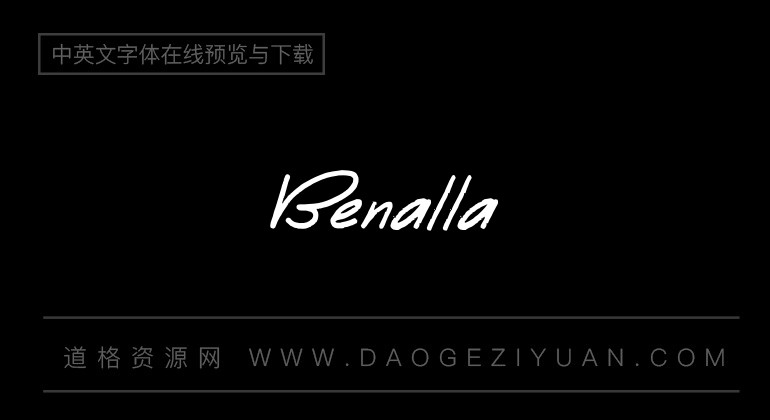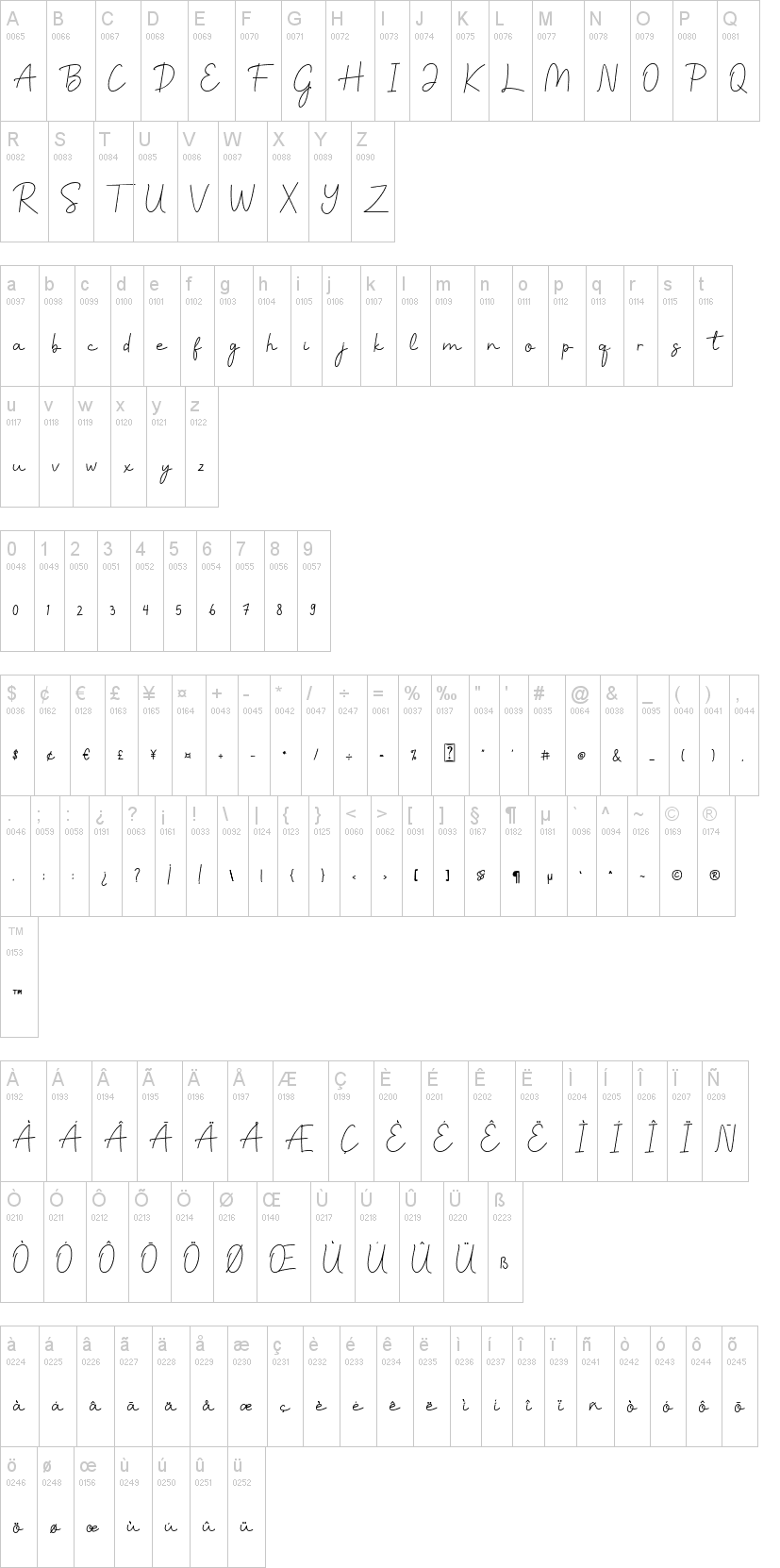
Benalla
Benalla 字体是一款现代多功能欧美字体,由荷兰设计师Lucas de Groot专为Monotype公司设计。Benalla字体具有精细的细节设计,且较为细腻,易于识别,使用起来非常方便,且具有良好的可读性。Benalla字体适用于各种设计领域,如标题、封面、印刷品、网页等,可用于任何专业设计项目。此外,它还具有良好的伸缩性,可以使用在各种分辨率的屏幕上,从而更好地满足多种设计需求。
Benalla是一款非常不错的手写艺术字体,具有很好的视觉感,适合于文化类的宣传设计、商业类品牌的广告和产品包装设计以及个性化文字排版等较多场景。
Benalla字符映射图